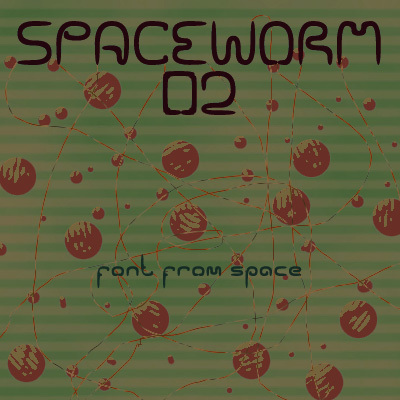
Spaceworm 02 di Eric Wiryanata è un font display gratuito in stile fumetto, caratterizzato da un ritmo elastico, quasi sinuoso, e da un tocco di fantasy rétro. Le lettere si arricciano, si piegano e si allargano in modo irregolare, rendendo le maiuscole morbide e vivaci anziché geometriche, con lunghi tratti a uncino e curve arrotondate che ricorrono in tutto il set.
È perfetto per poster, loghi di giochi, copertine di libri per bambini, grafiche per feste di Halloween, titoli di fanzine e brevi scritte dove questo font gratuito può dettare il mood da solo. Usalo per titoli, iniziali o monogrammi quando cerchi un lettering fluido e animato, senza scivolare nei soliti cliché horror.
Questa è la seconda versione di Spaceworm, un font che ho creato. Con un look un po' più "vermicelloso".